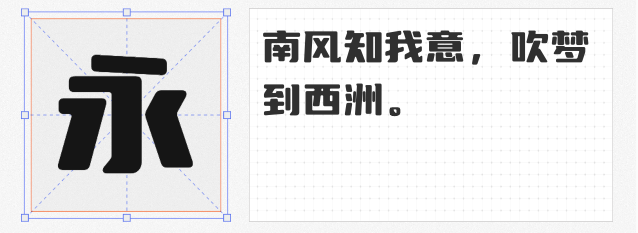
海报设计的核心在于视觉冲击力,而字体作为信息传递与风格营造的关键元素,往往能决定作品的成败。以下四款免费商用创意字体,以独特的设计语言和极高的适配性,为海报设计注入鲜活生命力,助力品牌快速吸引目光。
基于人气字体“优设标题黑”优化升级,优设标题圆将尖锐的棱角转化为柔和圆角,在保留力量感的同时,增添了一份亲和力。笔画粗细对比强烈,结构紧凑却不失呼吸感,尤其适合科技、生活类海报的标题设计。无论是电商促销的醒目主标,还是活动海报的温暖标语,圆角设计都能弱化攻击性,传递友好、包容的品牌态度,让信息传递更具温度。
站酷快乐体以“可爱有趣”为核心理念,笔画弯曲如笑脸,字形活泼似跳跃。每个字符都自带情绪感染力,特别适合针对Z世代群体的海报设计,如潮玩展、音乐节、快消品推广等场景。其不规则的笔画处理与夸张的变形设计,能瞬间打破画面沉闷,营造轻松、欢乐的视觉氛围,让海报自带“社交传播基因”。
站酷小薇LOGO体以“剑身”为灵感,笔画修长如刃,谦和灵秀中暗藏锋芒。通过简化部分笔画(如“口”字结构),在保持高识别性的同时,赋予字体轻盈的呼吸感。这款字体尤其适合品牌升级海报、文化展览主视觉等需要传递精致感与专业度的场景,既能凸显品牌调性,又能通过独特字形在信息洪流中脱颖而出。
斗鱼追光体2.0以“追光”为概念,转角处采用圆弧处理,包围结构笔画加入切口设计,既弱化机械感,又保留科技字体的未来感。中宫较大(字符内部空间开阔)的设计,确保远距离阅读依然清晰,非常适合游戏、互联网、科技类海报的标题与副标。其动态的笔画形态,能巧妙呼应“光”的流动感,为画面注入速度与能量。